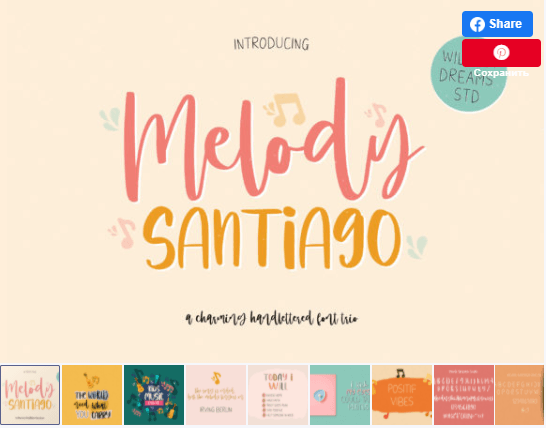
Melody Santiago Font
Melody Santiago - очаровательный и милый рукописный шрифт с 3 вариациями стиля. Благодаря своему лаконичному и простому стилю, подходящий для самых разных дизайнов, этот шрифт может стать вашим любимым шрифтом в любом случае!